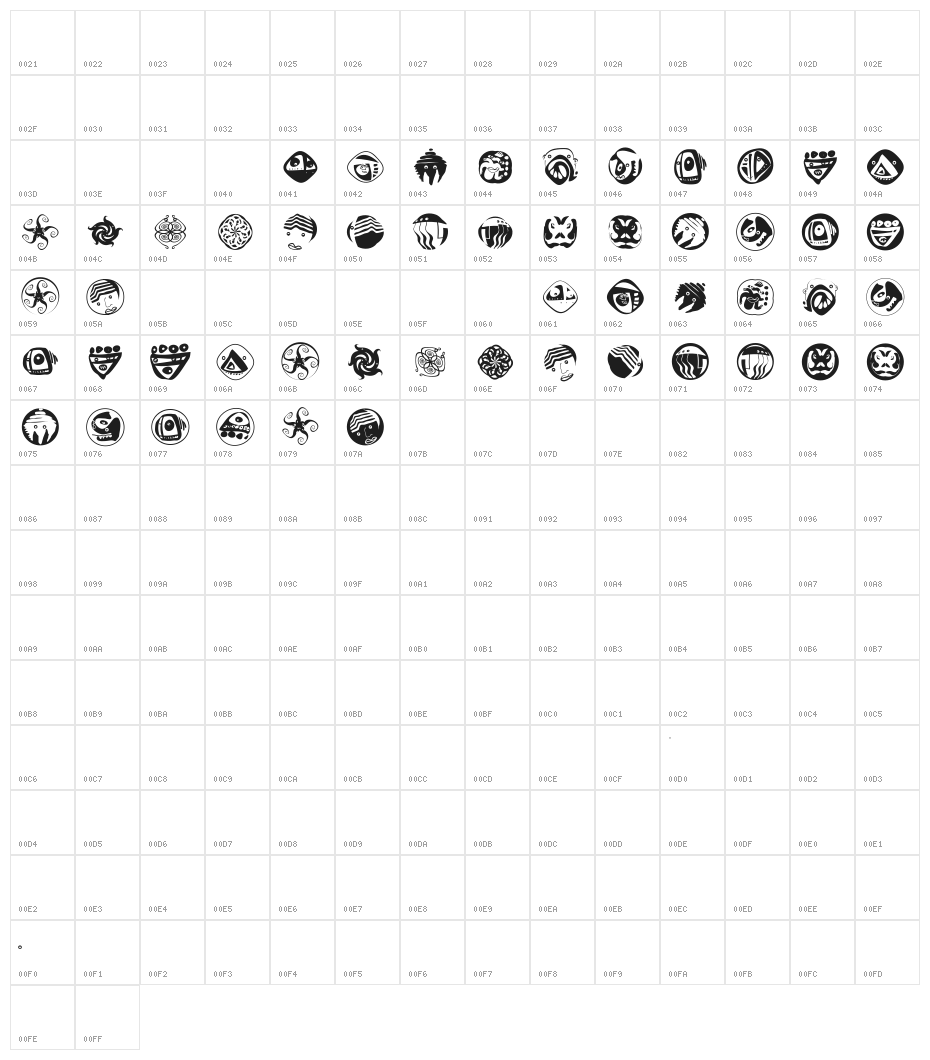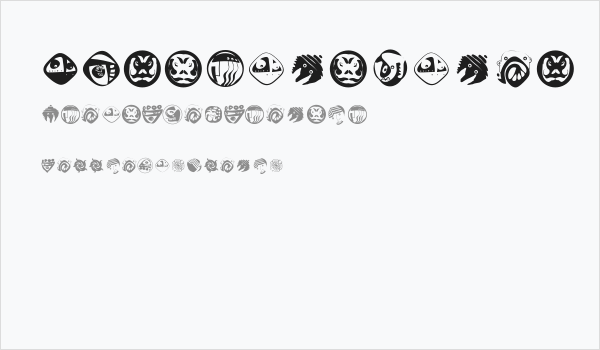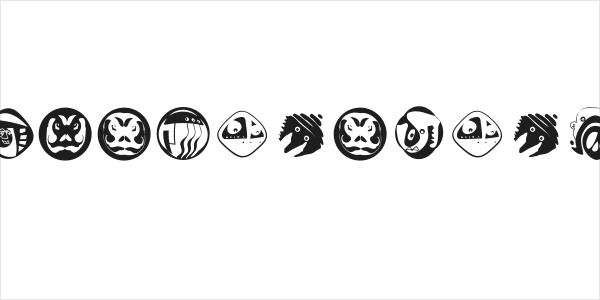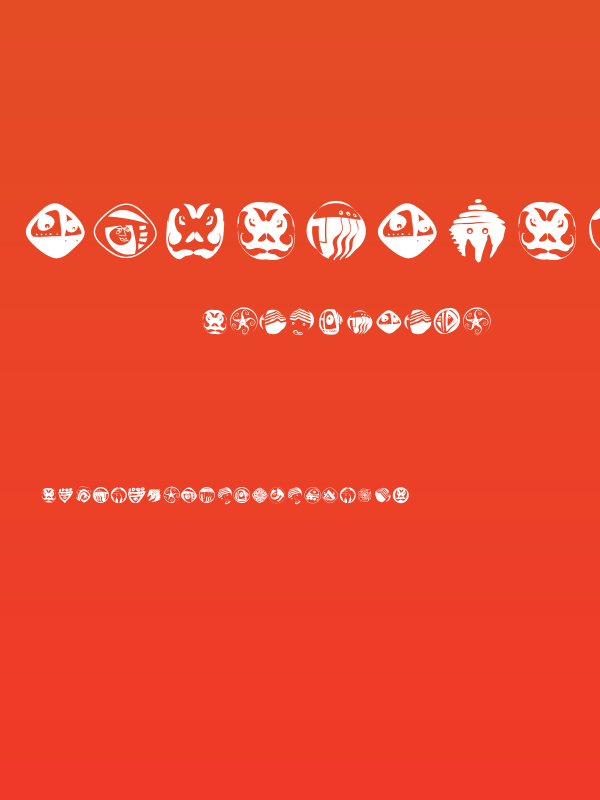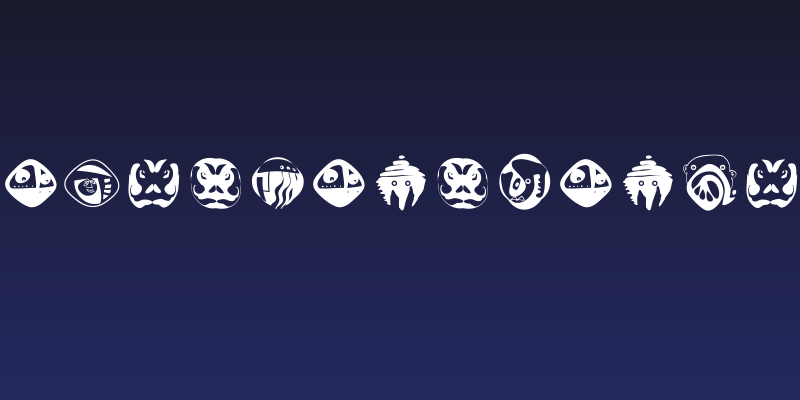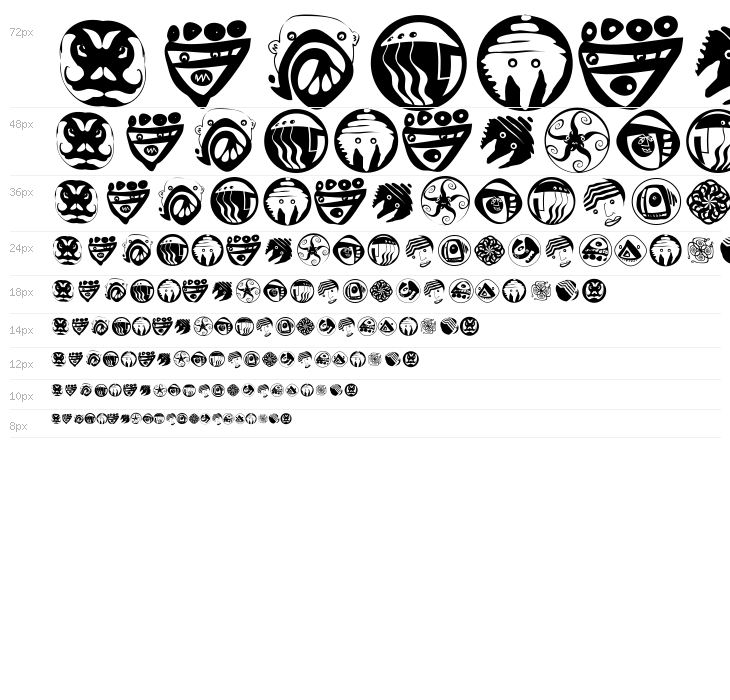
AbstractFaces Font
| Anwendungsfall | Logos, Artistic prints, Decorative motifs |
| Vorgeschlagene Projekte | Ideal for use in graphic design projects, such as logos, posters, or artistic prints. Suitable for creating unique branding elements or decorative motifs. |